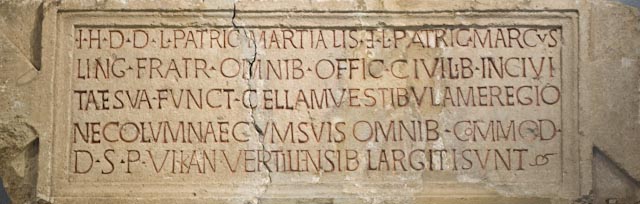
- Subject: [typo] Origine feuille aldine ?
Un tour au musée archéologique de Dijon permet d'admirer, outre une redoutable « muséographie » (1), quelque inscriptions & parmi celles-ci, celle-là :
La composition se concluant par :
La Renaissance étant férue de classicisme antique, le signe final m'a fait penser à la feuille aldine. Relisant du coup l'article paru dans Graphê n°30, juillet 2005, p. 13-19. « Pour une typologie de la feuille aldine par Max Caflish » dont l'adresse fut offerte sur cette liste, je n'y trouve pas mention de l'origine du signe, cela n'étant pas le sujet traité.
Y a-t-il effectivement lien, ou non ? Quelle doc. éventuelle existerait à ce sujet (là, impossible de consulter les archives de LaListe) ?
1. En plus de l'habituel & lamentable éclairage à contremploi, des reflets parasites et partout, une des trouvailles les plus originales semble bien être du bois sombre imitant à merveille le Formica imitant le bois, et sur lequel sont déposés des expôts eux-mêmes sombres.
Ceci dit, c'est dans ce musée qu'on peut voir, entre autre, les fabuleux bois sculptués du sanctuaire des sources de la Seine.